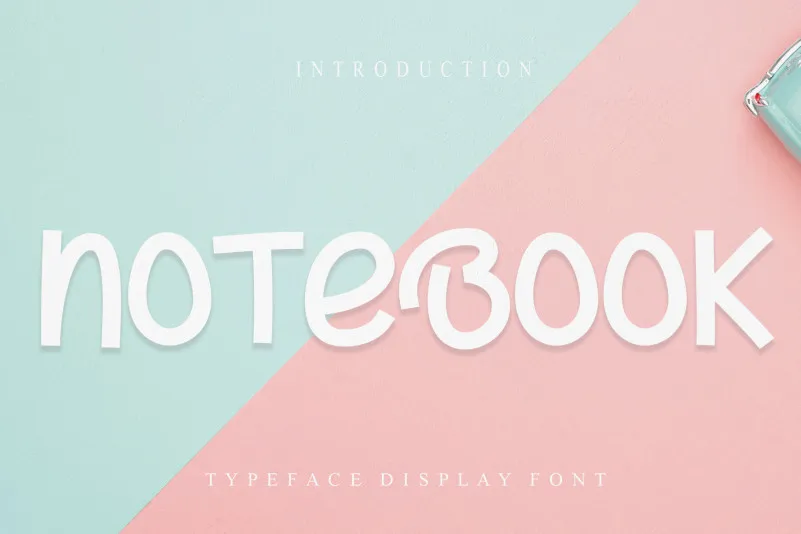
Esta fonte Notebook Display Font é perfeita para quem busca criar designs únicos e decorativos. Sujeitamente criada pela designer especializada creativeletter, essa fonte oferece uma experiência de leitura única e estética avassaladora. Com um design cuidadosamente elaborado que se adapta a várias tarefas gráficas, é perfeita para aqueles que desejam dar o seu trabalho um toque singular. Seja você criando materiais publicitários, elementos de logomarca ou qualquer outro tipo de design visual, esta fonte Notebook Display Font será um recurso invaluable ao seu arsenal. Ela traz uma dose extra de personalidade à sua arte digital e pode ajudá-lo a destacar na multidão de criativos contemporâneos. Não deixe de experimentar essa deliciosa adição à sua biblioteca de recursos gráficos para criar designs que se tornam verdadeiros exemplos de talento visual.